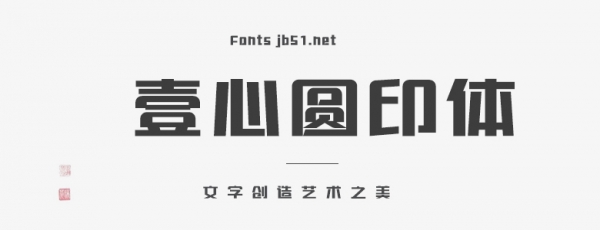
壹心圓印體是一款創(chuàng)意的簡(jiǎn)約力量型字體,適合應(yīng)用于藝術(shù)設(shè)計(jì)、平面宣傳設(shè)計(jì)、網(wǎng)頁(yè)設(shè)計(jì)、書(shū)法字體,海報(bào)設(shè)計(jì)等領(lǐng)域,歡迎喜歡這款字體的朋友下載收藏 。